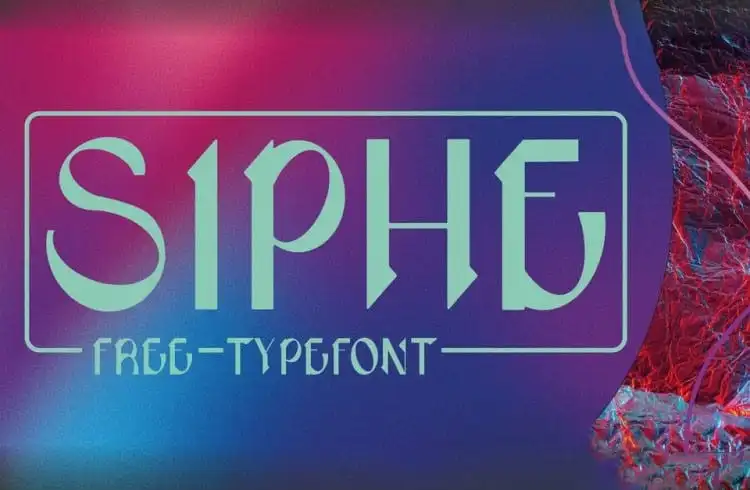
Siphe Display Font – Download Grátis
A Siphe Display Font surgiu inspirada nos caracteres pre-Carolingian uncial que datam mais de mil anos. Criada e compartilhada pela designer Eve Perrin, essa tipografia é perfeita para desenhos de logomarcas, artefatos publicitários, capas de álbuns e uso editorial. Com contraste alto e formas de letras distintivas, a Siphe oferece um visual moderno e único, ideal para estilos visuais inovadores. Sujeito ao seu gosto pessoal, essa fonte trará uma aparição única a qualquer projeto onde for usada.